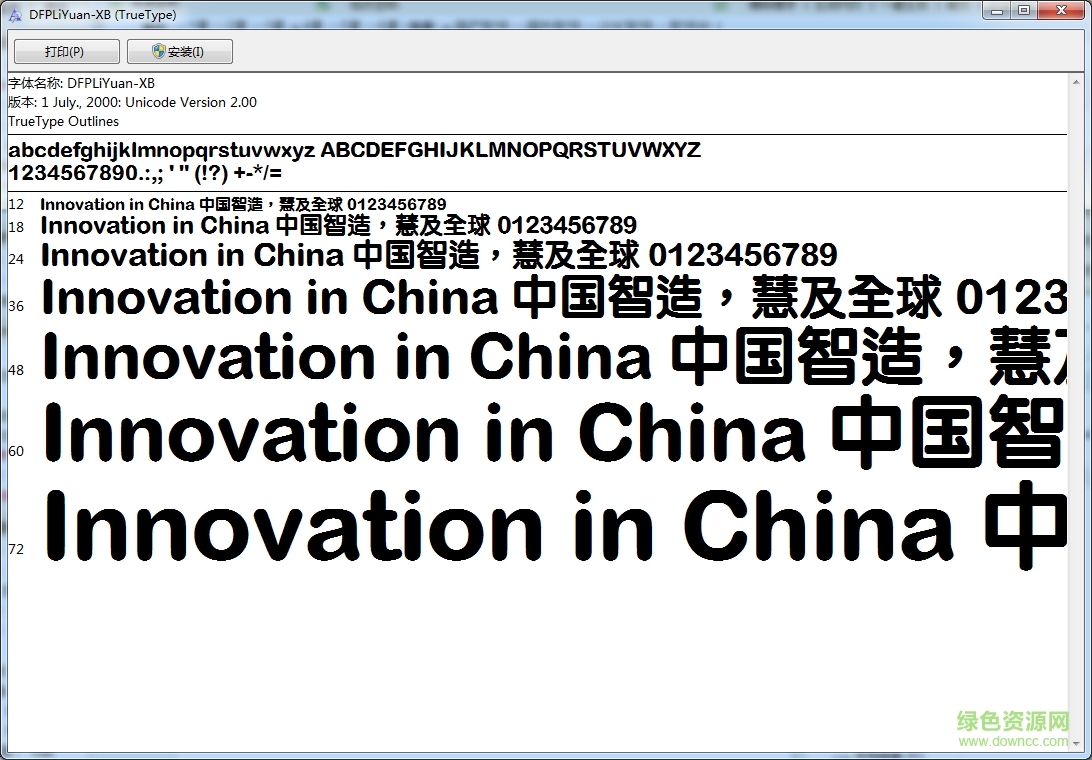
華康儷特圓是一款應(yīng)用于廣告設(shè)計方面的簡體中文字體,該字體線條粗壯有力,字形端正大方,整體效果非常出眾,且字庫完整,可以適用于名片設(shè)計、平面設(shè)計、廣告設(shè)計、報紙雜志、企業(yè)LOGO、商標(biāo)注冊、電視臺廣告等領(lǐng)域,使用時請選擇“DFPliYuan-XB”即可,有喜歡的網(wǎng)友可免費下載收藏。